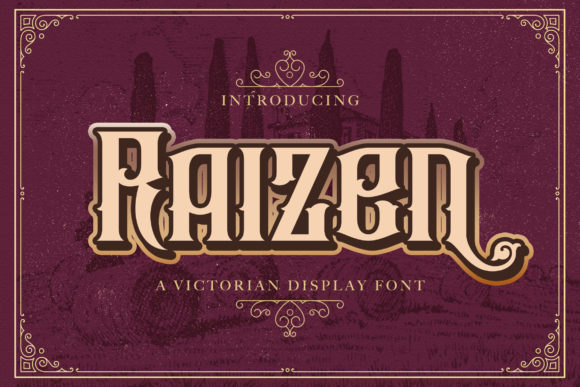
Raizen - невероятно смелый и круто выглядящий шрифт с черными буквами.
Этот шрифт идеально подходит для написания юридических документов, писем и всего остального, что требует выразительности и напористости.